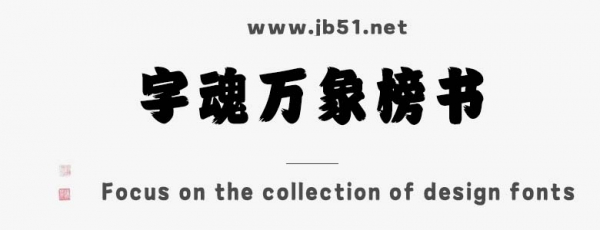
字魂萬(wàn)象榜書(shū)是由字魂字庫(kù)推出的楷體字體,該包含9503個(gè)中文、字母、 符號(hào)和數(shù)字,具有復(fù)古傳統(tǒng)的風(fēng)格,可以滿足您設(shè)計(jì)上的各種需求,適合應(yīng)用于藝術(shù)設(shè)計(jì)、平面宣傳設(shè)計(jì)、網(wǎng)頁(yè)設(shè)計(jì),書(shū)法字帖等領(lǐng)域。
字魂萬(wàn)象榜書(shū)字體是一款商用的楷體字體,該字體包含9503個(gè)中文、字母、 符號(hào)和數(shù)字,具有復(fù)古傳統(tǒng)的風(fēng)格,可以滿足您設(shè)計(jì)上的各種需求,該字體主要用于標(biāo)題等場(chǎng)景, 您不但可以在字魂網(wǎng)下載字魂萬(wàn)象榜書(shū)字體,同時(shí)還有眾多毛筆書(shū)法字體、創(chuàng)意字體等可供選擇!